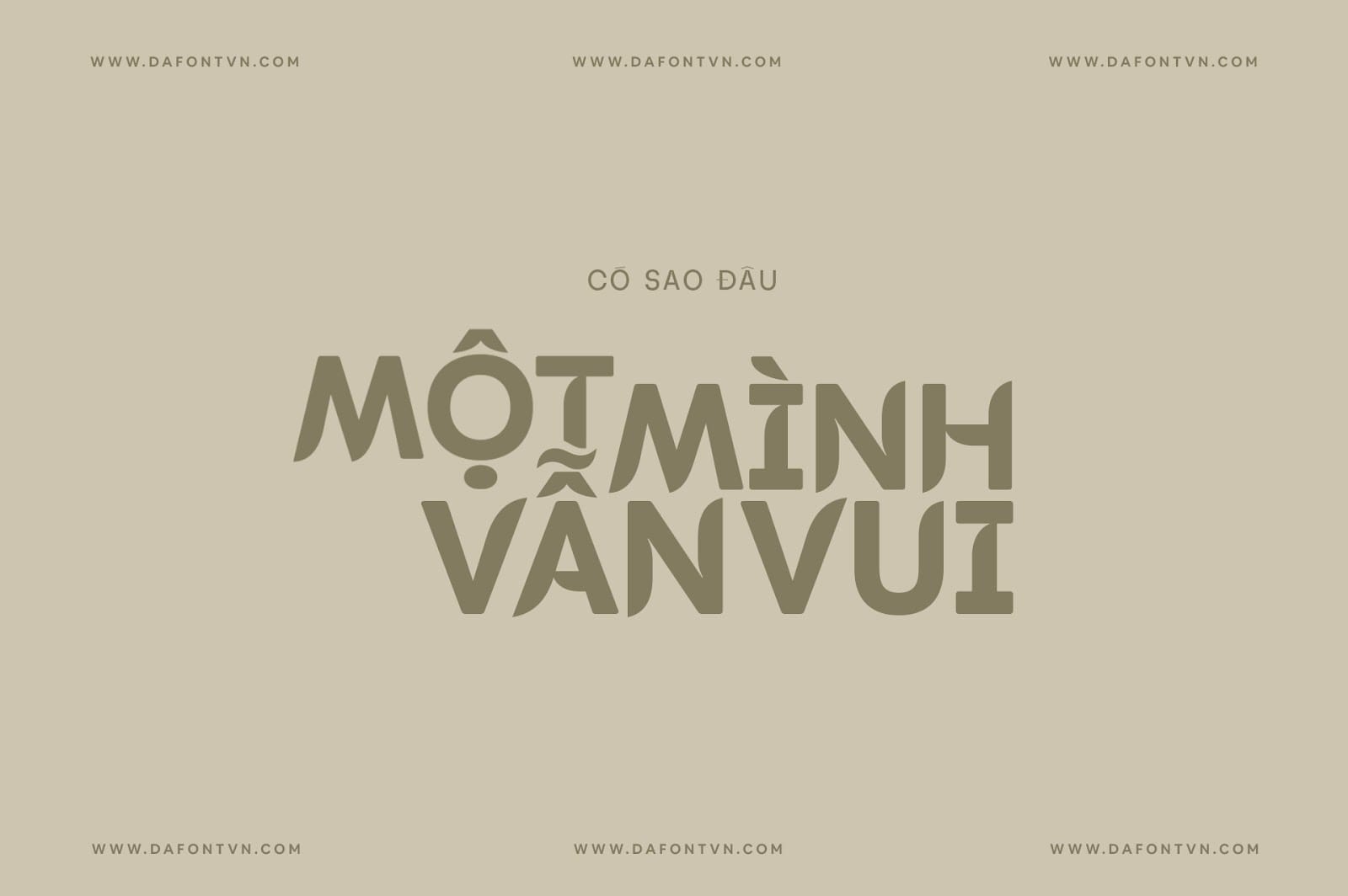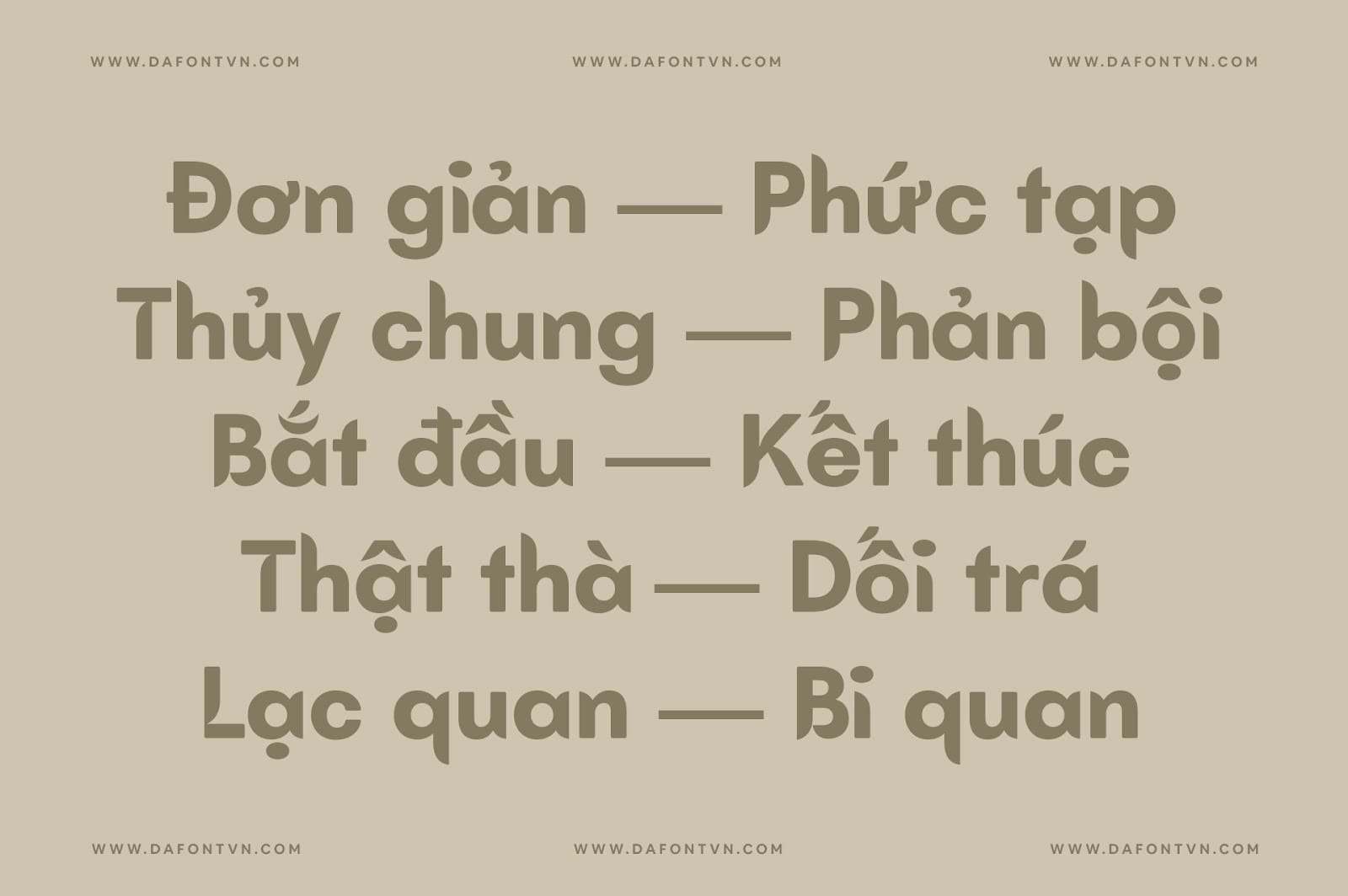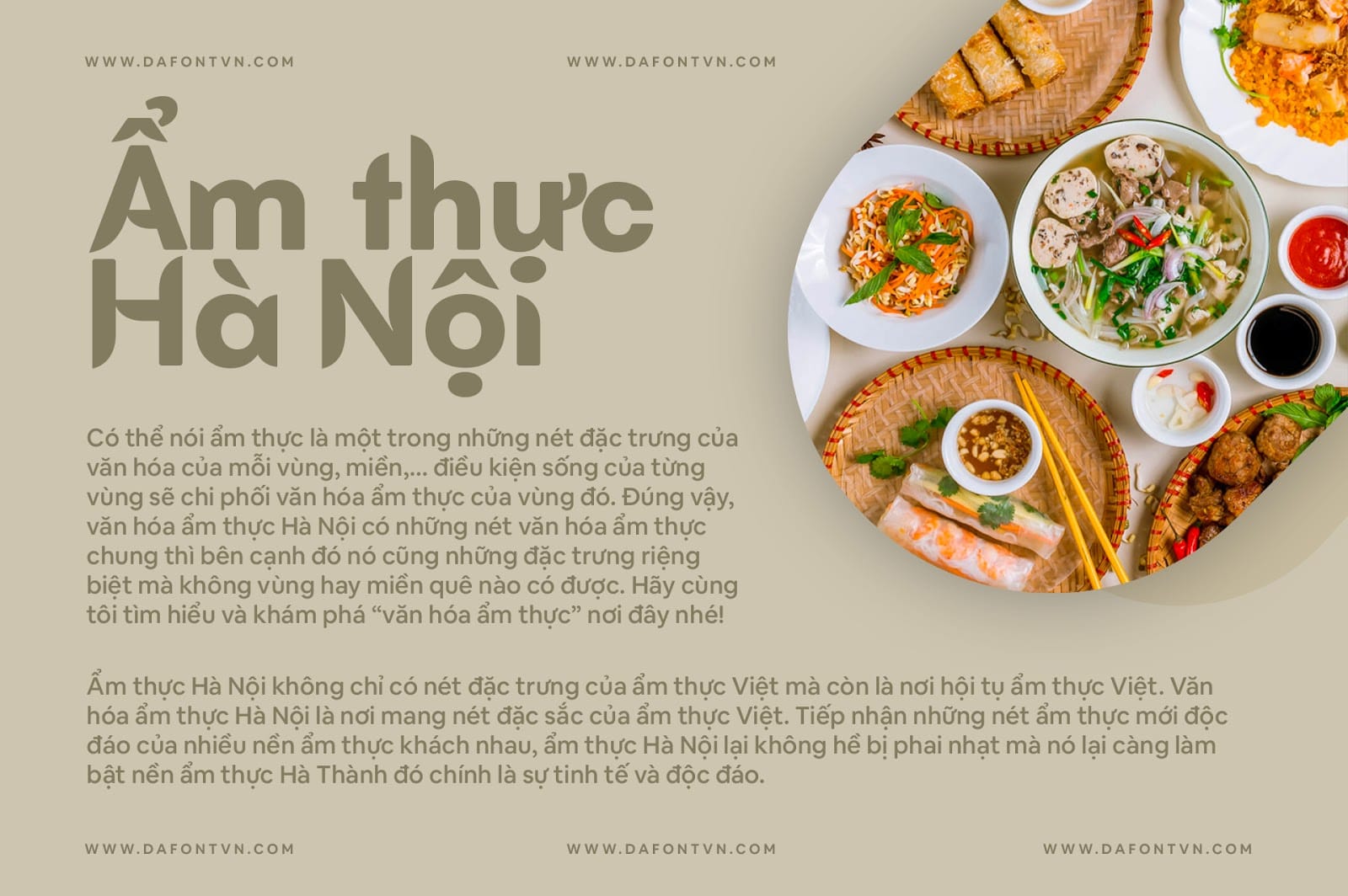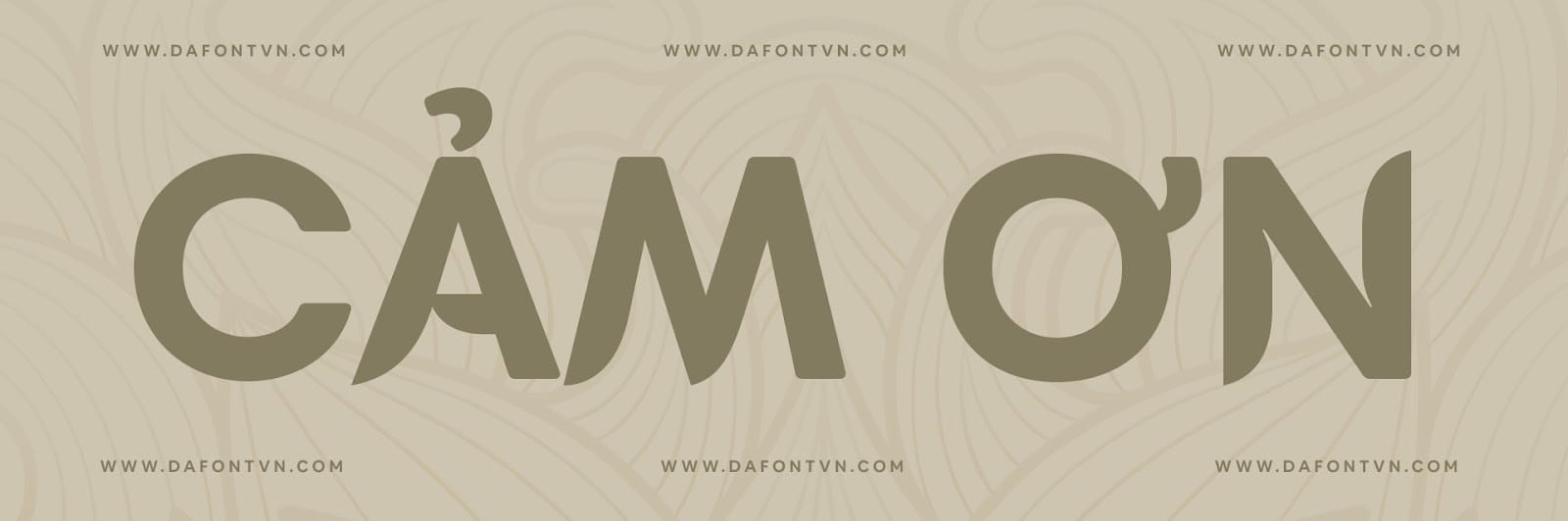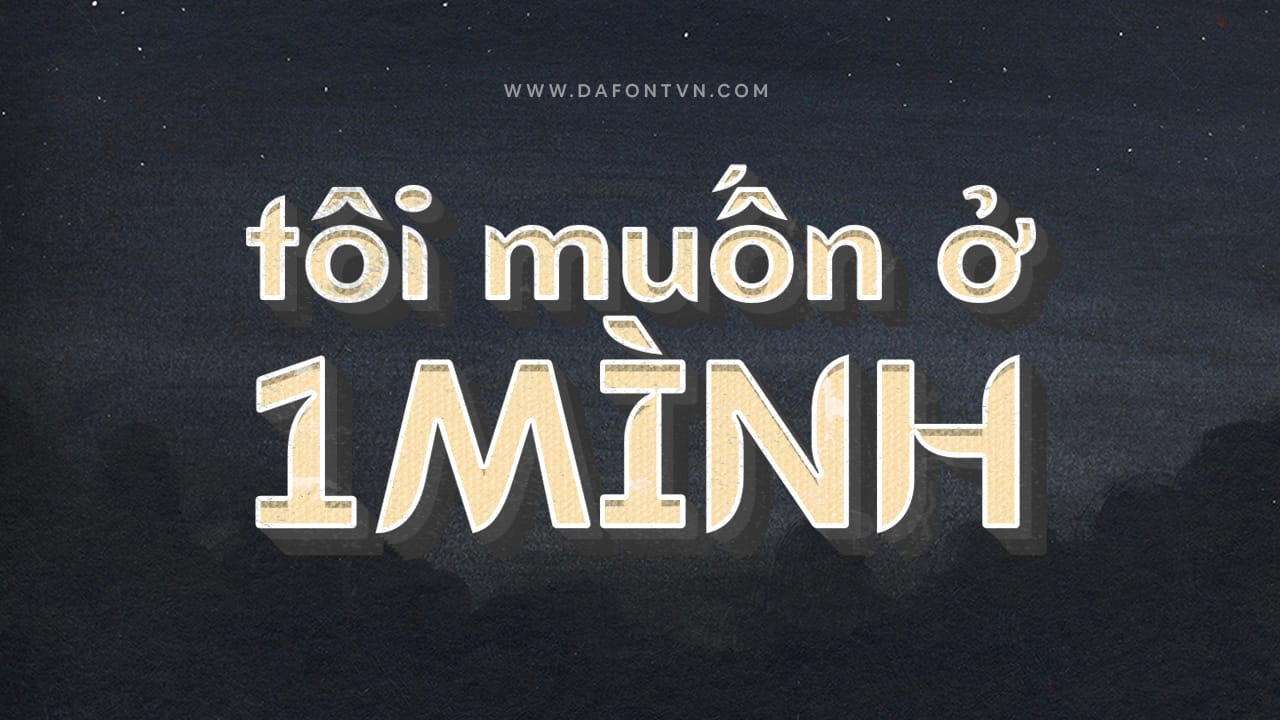
Batangas Font – Tên của font chữ được lấy tên từ một thành phố Batangas nằm ở Calabarzon, Philippines. Nơi đây là một địa điểm du lịch thú vị với ngọn núi lửa Taal nổi tiếng, những bãi biển hoang sơ, những điểm lặn, những di tích lịch sử và ẩm thực tuyệt vời.
Kiểu chữ Batangas được lấy cảm hứng từ tính cách mạnh mẽ của người dân Batangas. Điều này thể hiện rõ trong văn hóa, truyền thống và biểu tượng của họ. Font chữ với các nét đậm ấn tượng được hiển thị tốt ở kích thước lớn.
Font Batangas có sẵn dấu tiếng Việt và phù hợp cho các thiết kế như tiêu đề, logo, biểu trưng, poster, thiệp mời, bìa sách, font chữ này cũng rất phù hợp để sử dụng cho những thiết kế cổ điển và hiện đại.